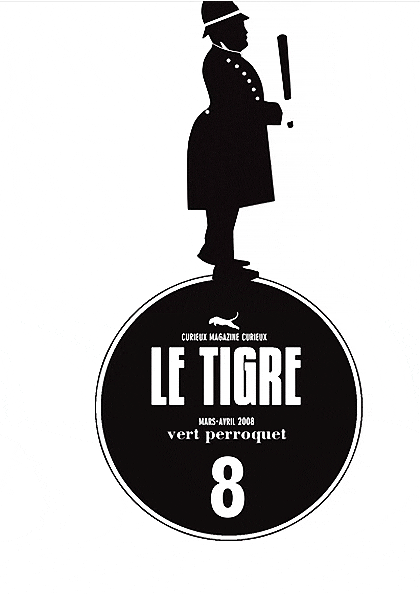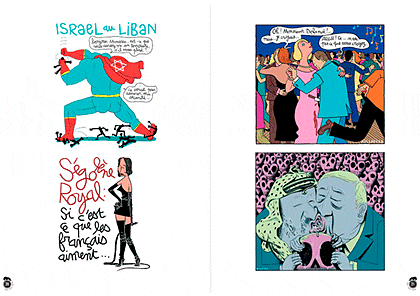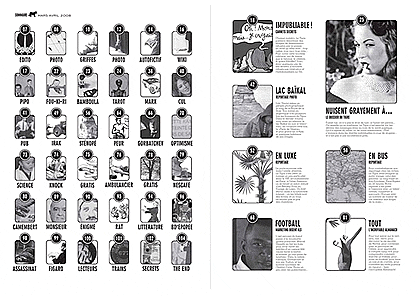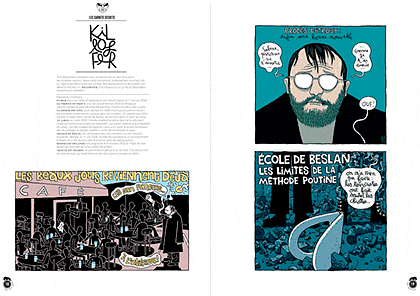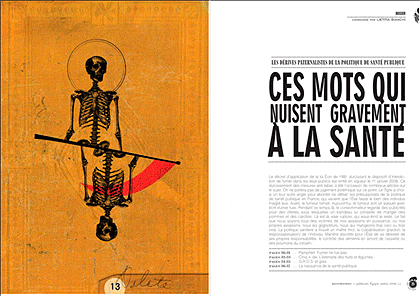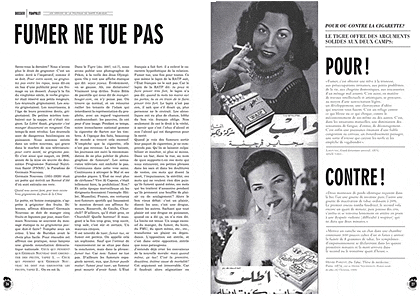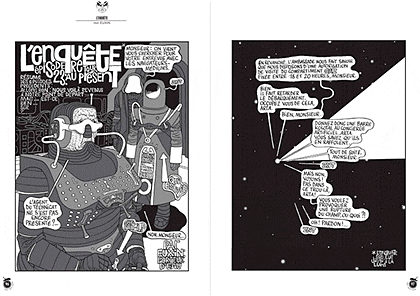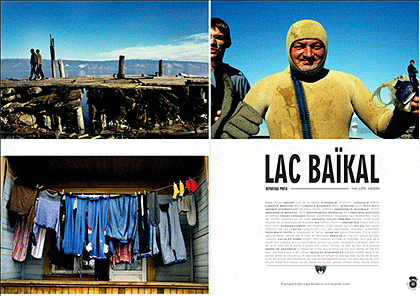
Typographie du Tigre | la nouvelle maquette est disponible
J’ai toujours eu une grande tendresse pour la démarche littéraire d’un magazine. Déjà je participais (comme simple typographe) à l’élaboration de l’Autre Journal (Michel Butel) ou au «Monde Illustré» qui devait sortir à la fin des années 80. Ce dernier n’a finalement jamais vu le jour à l’exception de deux numéros zéro, cependant on peut supposer que le Monde II est l’émanation de cette époque où les quotidiens voulaient être également présents sur le segment des hebdos.
Qest-ce que le Tigre?
«Le Tigre est un magazine généraliste indépendant et sans publicité, distribué en kiosques et en librairies. Le Tigre est dirigé par deux auteurs, Lætitia Bianchi et Raphaël Meltz. Des journalistes, photographes, dessinateurs, écrivains et universitaires participent au Tigre. Dans la lignée des grandes aventures de presse magazine des trente dernières années (Actuel, l’Autre Journal), Le Tigre propose un regard singulier, rare, à contre-courant de l’uniformisation ambiante.»
Pourquoi Le Tigre?
«Avant de créer Le Tigre, Lætitia Bianchi et Raphaël Meltz ont dirigé R de réel, une revue «alphabétique» (de A à Z, 2000-2004, www.rdereel.org) qui a bénéficié d’un très bon accueil auprès des critiques et des lecteurs. R de réel mélangeait les sciences humaines, la littérature et l’illustration, le tout dans une maquette dadaïste… À la fin de l’alphabet, une idée est venue: pourquoi pas un projet aussi téméraire, mais cette fois dans le secteur de la presse?
C’est ainsi qu’est né Le Tigre en mars 2006. Le Tigre dresse des passerelles entre des secteurs d’ordinaire très éloignés. Le Tigre revendique d’être inattendu, inclassable, à la fois léger et sérieux, inventif et rigoureux, parfois sauvage… mais toujours curieux dans les deux sens du terme. C’est pourquoi Le Tigre est un magazine à la personnalité très marquée, et c’est pourquoi Le Tigre a pris le parti de ne pas faire ce que d’autres font déjà très bien:
— Le Tigre ne fait pas de recension de l’actualité culturelle (livres, films, disques, etc). En revanche, Le Tigre fourmille de créations d’auteurs contemporains (pages graphiques et dessins, photographies sans contrainte d’actualité, etc.)
— Le Tigre est un journal critique, mordant à l’occasion, mais qui préfère l’ironie à la diatribe, n’est jamais défaitiste, et ne se revendique délibérément d’aucune mouvance politique. Le Tigre a l’ambition de faire réfléchir et non de dire ce qu’il faut penser…»
J’ajouterai que le Tigre dirigé par Raphaël Meltz et Lætitia Bianchi file dans la droite ligne du mouvement DaDa lancé par Hugo Ball en 1915. Autant littéraire que graphique le mouvement essaima à travers toute l’Europe et prit différents visages que ce soit sous le marxisme en Russie ou le Bauhaus de Weimar ou encore les mouvement surréalistes d’André Breton et plus récemment l’Oulipo pouvait se revendiquer de même du mouvement suisse. Scénariste, écrivain Raphaël Meltz est avant tout un curieux, un chercheur d’idées introuvables. Sa démarche narrative est donc bien avant que d’être graphique de l’ordre de l’écriture. Ce faisant quand on regarde la revue Tigre on est surpris de ne pas retrouver les codes de la modernité 2.0 magnifiquement illustré par le magazine Ink. Il ne faut cependant pas s’y tromper la démarche est la même à ceci près que le contenu prime sur la forme. Un tout petit peu. Une forme décalée, presque rétro pour ceux qui ne regardent pas au détail. Je vous laisse en compagnie de cette nouvelle maquette et si vous voulez en découvrir plus et dans un format plus confortable, rendez-vous sur le site du Tigre où l’on vous donnera les recettes de la lecture.
à propos de l’universalisation de la typographie dans les magazines (j’ai lu ton article de vendredi) je vais te raconter ceci :
En 1968, je venais de transformer le Figaro littéraire en magazine (modeste, nous ne disposions pas de la couleur) après avoir été alerté par Bernard Pivot des intentions de Match de s’en emparer.
C’était alors la guerre entre Hersant et les propriétaires du journal. Bref, voilà mon Littéraire reparti avec une nouvelle typo : le Clarendon ; la composition se faisait encore en plomb dans le sous-sol de l’immeuble du Rond-Point des Champs Elysées. Le tirage est à cette occasion passé à l’offset d’après des épreuves sur cello, un trafic pas possible !
C’est à ce moment que Robert Ranc (directeur de l’Ecole Estienne) me propose de changer de crèmerie, après 10 ans de Figaro, pourquoi pas…
Et me voici D.A. de Réalités revue prestigieuse, certes, mais je me suis vite aperçu de mon erreur. Logée dans l’immeuble de l’Illustration,dans des locaux vétustes et surtout les bureaux étaient répartis de chaque côté d’un couloir, toutes portes fermées ; pas de salle de rédaction, pas de communication hors la réunion hebdomadaire chez le rédac-chef.
L’équipe de maquettiste assez basique et pas de moyens : le titrage se faisait en Letraset !! Mon souhait de les commander chez Typogabor ou chez Albert Hollenstein fut repoussé et a fortiori celui de choisir une typographie de mon choix. La photocompo se faisait rue Montmartre et l’impression chez Danel à Lille.
Au bout de 3 mois Robert Ranc me demande de faire une communication à Estienne devant un aréopage de professeurs où il faisait l’apologie de la typographie française.
Il comptait sur moi pour faire de Réalités un exemple dans ce domaine.
Je fus obligé de révéler que dans ce cas, le graphiste que je croyais être n’avait aucun pouvoir d’intervention : les polices étaient celles de la machine affectée à la revue, quant au titrage je lui ai révélé la réalité en des termes certainement véhéments.
Pierre Faucheux, à la sortie, m’a confié n’avoir pas souhaité travailler avec la presse, Finel itou.